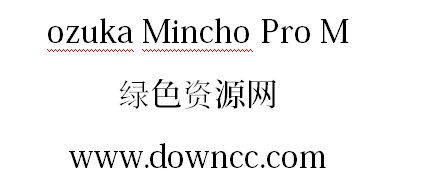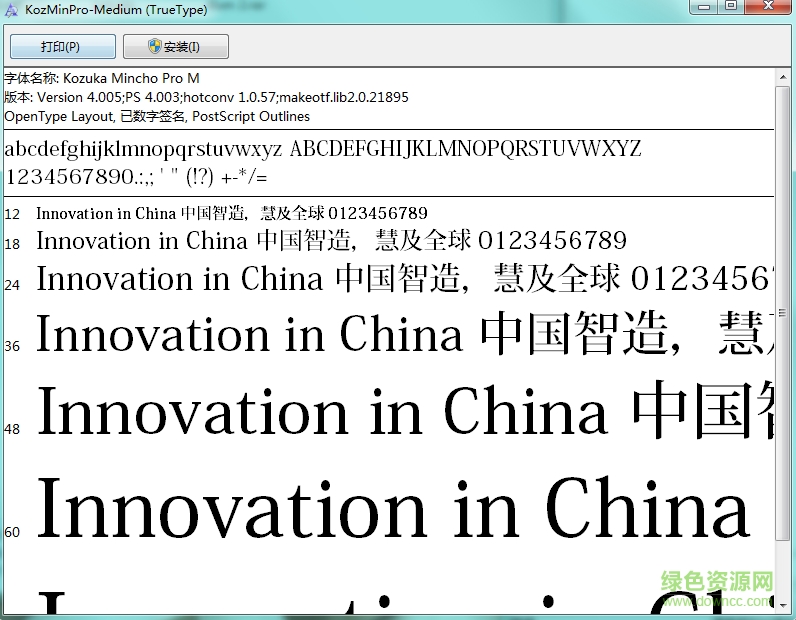
小冢明朝 pro是一款日本明細(xì)體,是小冢明朝字體的升級(jí)版,自己秀麗明朗,有著明朝風(fēng)骨的獨(dú)特美感,讓你看起來(lái)很舒適很新穎,來(lái)綠色資源網(wǎng)即可免費(fèi)下載使用!
小塚明朝體Pro是日系匯總文字體,采用了宋體的娟秀風(fēng)格,端正壁紙,字庫(kù)完整不缺字,支持中文簡(jiǎn)體輸入,可廣泛使用于廣告設(shè)計(jì)、文字排版、藝術(shù)創(chuàng)作等領(lǐng)域。
小塚明朝舊字形 Pro-VI R字體家族系列主要提供Regular等字體風(fēng)格樣式。小冢明朝作為日本字體中比較受歡迎的藝術(shù)字體,保留明朝體的風(fēng)韻,更有襯線典雅的創(chuàng)新,深得網(wǎng)友喜歡。